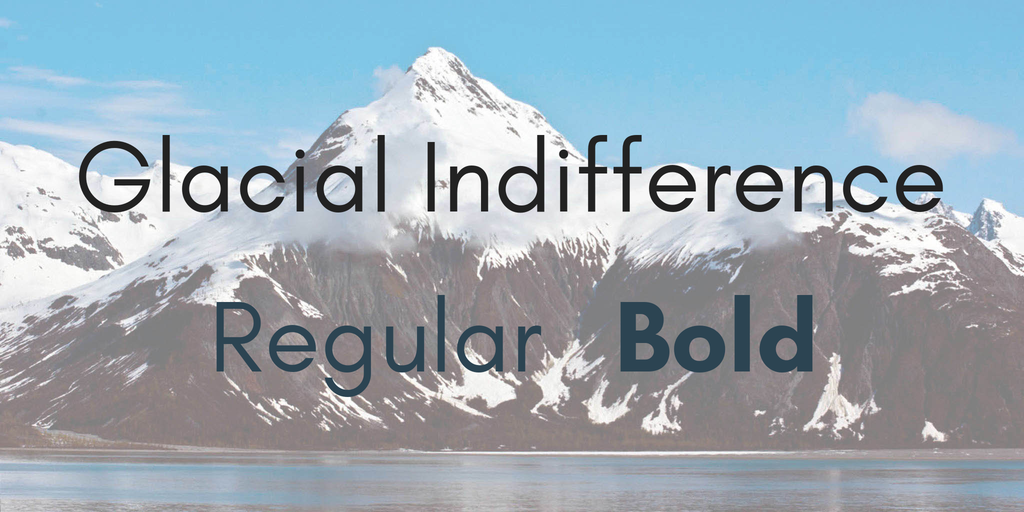
Glacial Indifference Font Family
A Glacial Indifference é uma fonte aberta inspirada no estilo geométrico de fontes Bauhaus. Esta família de fontes sans-serif é perfeita para criar designs minimalistas e modernos, ideal para aplicativos digitais e websites onde um olhar ressecado e distante seja desejado. Inspirada nos círculos, quadrados e retângulos simples do Bauhaus, a Glacial Indifference oferece uma mistura elegante de modernidade e simplicidade. Suas linhas rígidas e puras remetem ao trabalho rigoroso da escola alemanha, enquanto se adequam perfeitamente às necessidades contemporâneas dos profissionais do design digital. Para quem busca a pureza de um tipo geométrico combinada com uma atitude distante e serena, Glacial Indifference é uma excelente escolha para projetos que buscam expressar esses valores no ambiente digital.